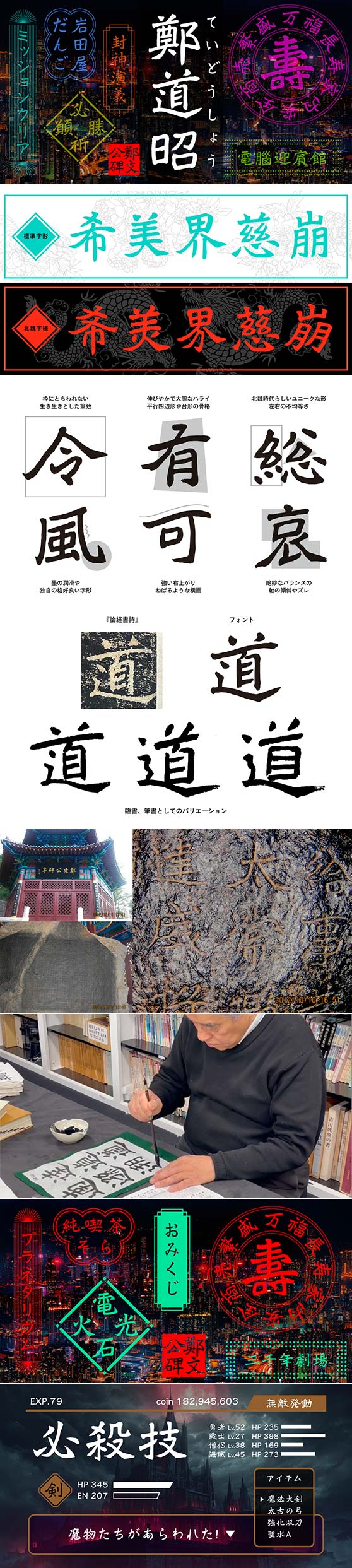
楷書体
イワタ鄭道昭 / イワタ鄭道昭北魏字様 StdN R
1500年前、中国雲峰山の岩壁に刻まれた鄭道昭の書が現代に蘇る。摩崖碑の風化や岩肌のニュアンスを封じ込めた書体。書家・大庭紀霽氏によって書き下ろされた、ゴツゴツとした力強さの中に、のびやかな骨格の優しさが光る独特のバランス。雄大な自然や筆の息遣いまで感じる、圧倒的な存在感を放つ書体です。
現代の標準的な字形に近い「イワタ鄭道昭」と、拓本に倣った「イワタ鄭道昭北魏字様」の2書体セットです。